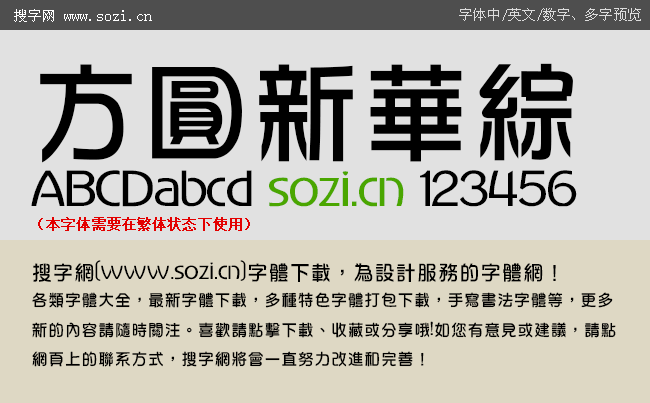
方圓新華綜
搜字網(wǎng)提供一款方圓新華綜中文字體下載,方圓新華綜體是一款中文藝術(shù)字體,字體由黑體為原形進(jìn)行變形設(shè)計,保持端正醒目風(fēng)格的同時略帶有廣告POP風(fēng)格。適合應(yīng)用于廣告設(shè)計、名片設(shè)計、包裝印刷、產(chǎn)品設(shè)計等應(yīng)用。